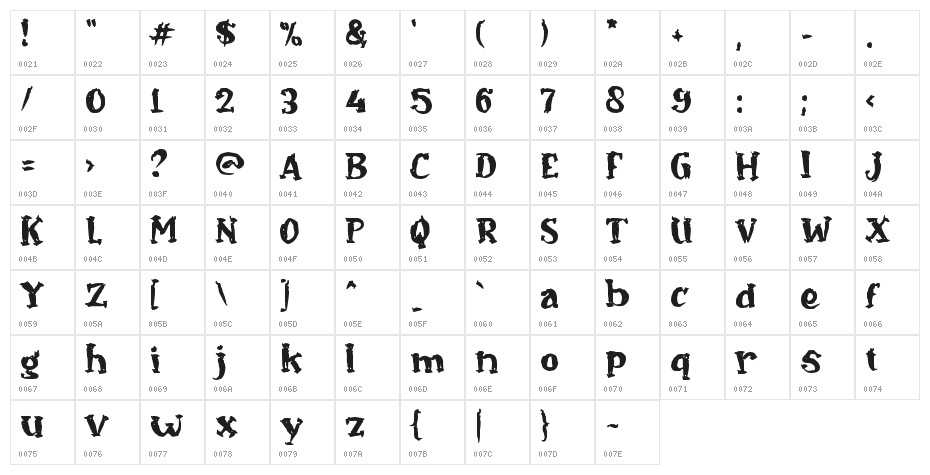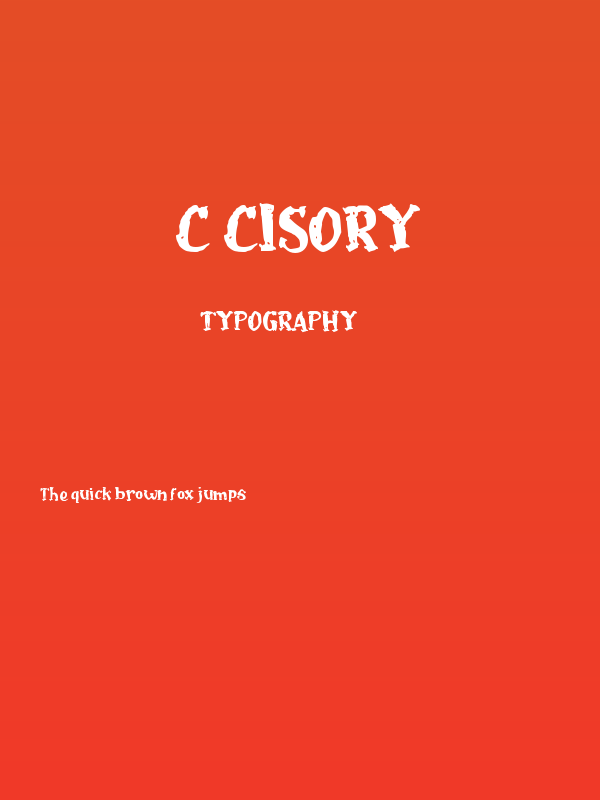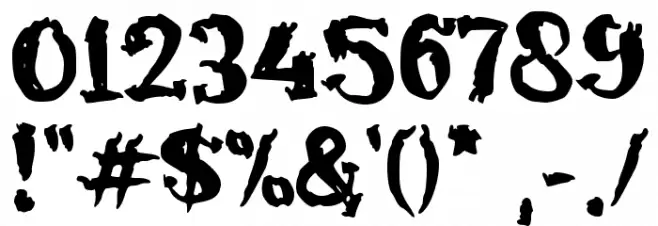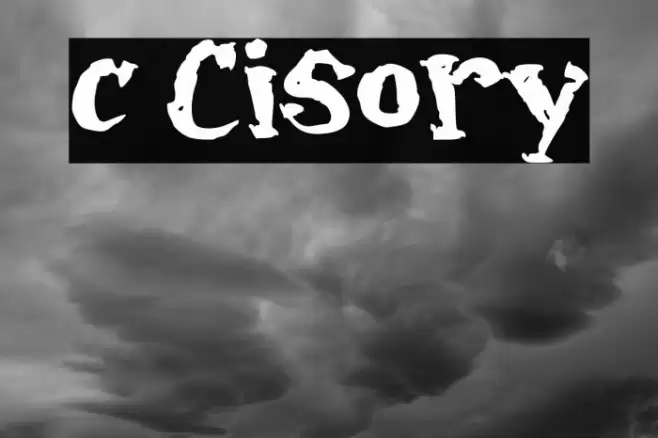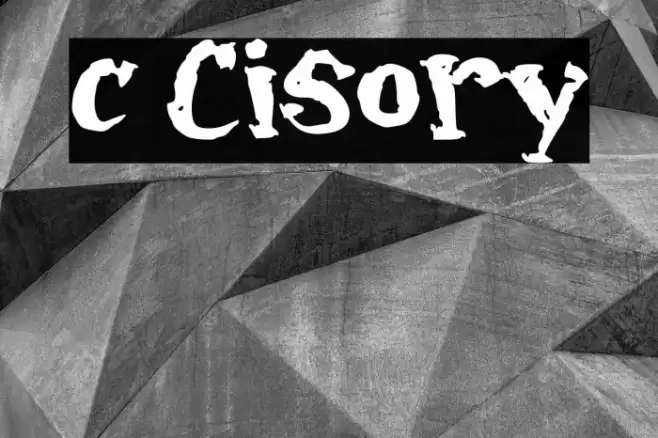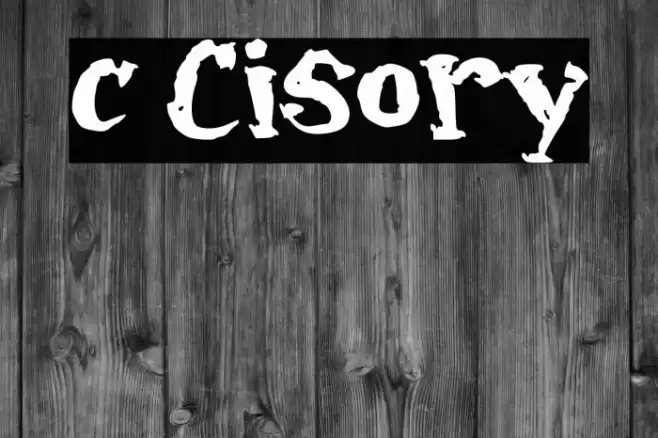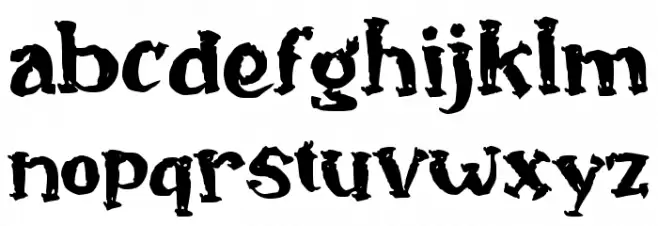
c Cisory Font
| Proyectos propuestos | Ideal for projects requiring a strong, edgy aesthetic such as posters, album covers, or branding for alternative or grunge-themed products. |